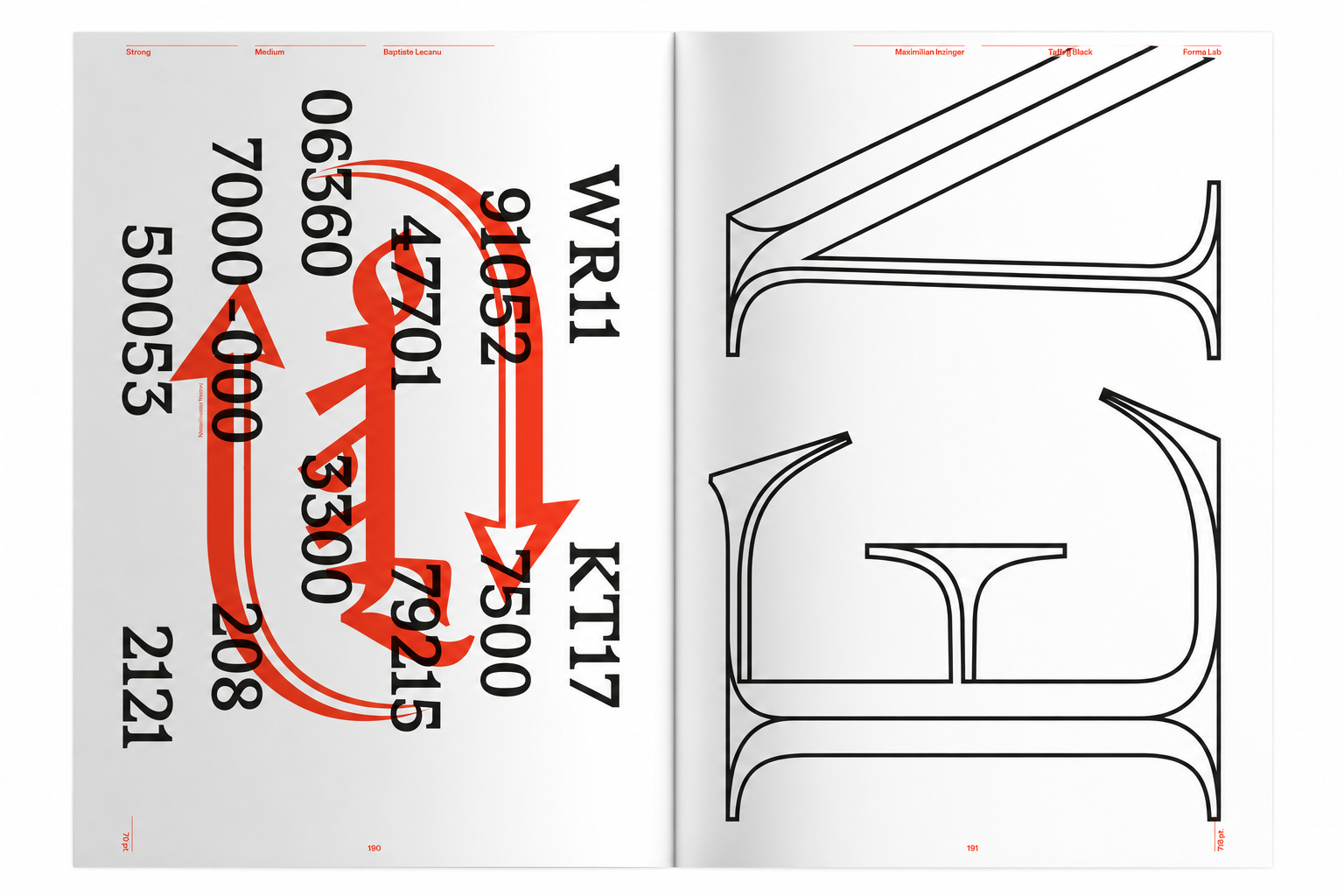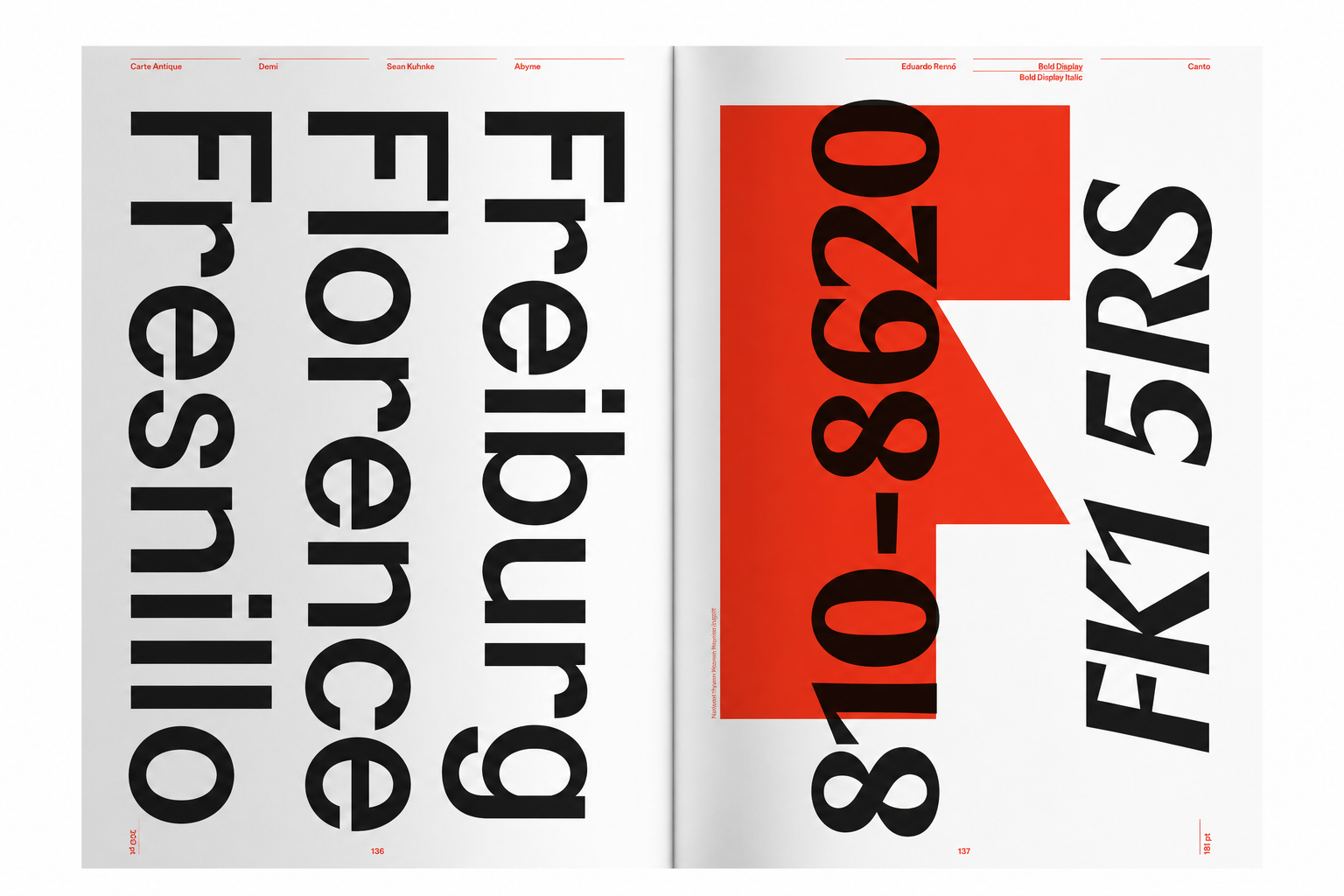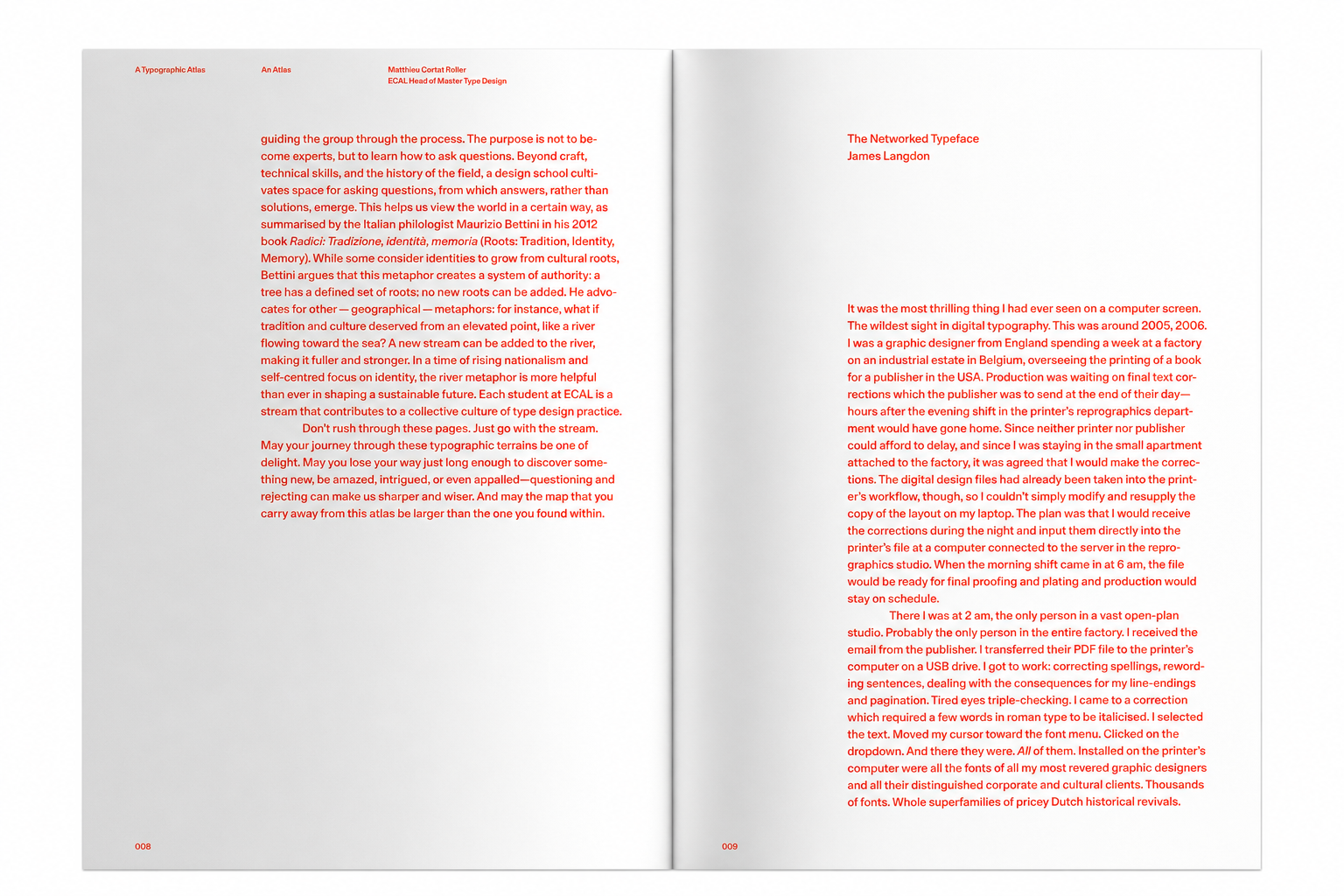
ECAL: A Typographic Atlas - more than 300 typefaces and their various styles
【書籍簡介】
字體樣本最初是印刷商與字體鑄造廠用來展示字型目錄的工具。早期多以單張形式出現,隨著工業化發展、識字人口增加,以及字體風格日益多元,逐漸演變為完整的出版物。到了今日,字體樣本大多轉向數位形式,而這本書則重新回到紙本,將字體展示、設計研究與教學成果整合在同一冊之中。
本書既是一部字體樣本集,也是一張字體創作的地圖,完整記錄洛桑藝術設計大學 ECAL 過去十年間的字體設計成果。來自學士與碩士課程的四百多位畢業生,透過字形繪製、字距調整與程式設計,持續探索字體在閱讀、觀看與使用上的各種可能。
書中收錄的作品橫跨經典正文字體、實驗性字形、多語文字系統與展示字體,呈現字體設計在形式、技術與文化之間的豐富面貌。這不只是一冊設計成果集,也反映出 ECAL 如何成為連結教學、研究與實務的重要平台,讓來自不同文化背景的字體觀念在此交會,展現當代字體設計的廣度與活力。